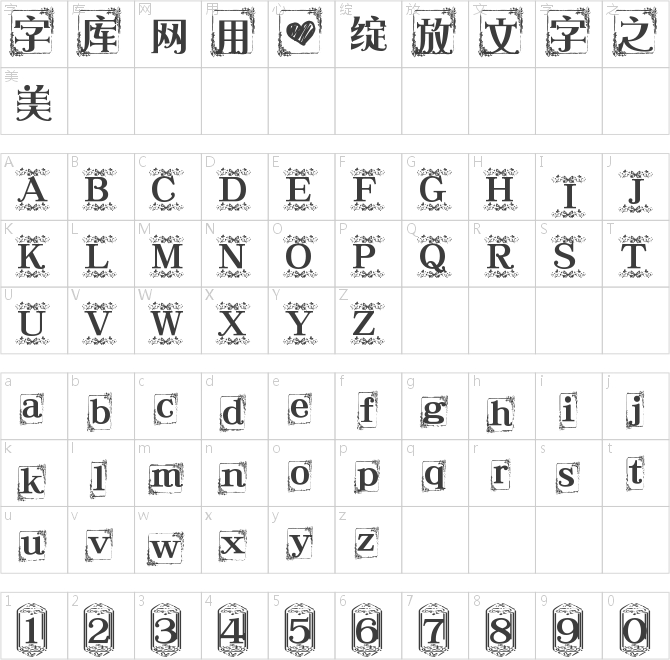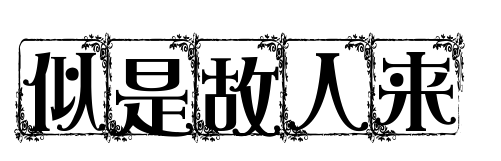
字體名稱: 似是故人來
作者版權: 大寧
似是故人來
似是故人來介紹
似是故人來字體似是故人來-by淺綠字庫是一款讓人賞心悅目、百看不厭的中文字體,適合各類廣告和產(chǎn)品包裝設計應用,字體大小16.02MB,格式為ttf字體,上傳用戶是Me / ,yD ,作者/版權方為大寧
似是故人來效果圖